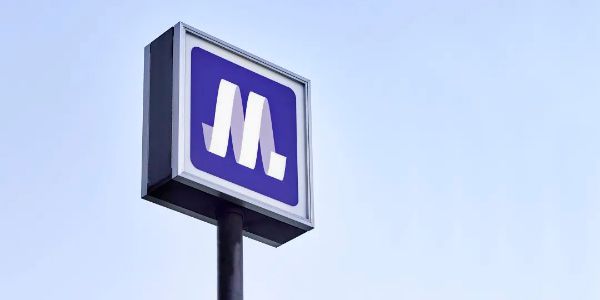
面对客户的致命三连,资深大叔教你从容应对
色部义昭的设计给我的感觉可以总结为两个字:“清爽”。这种清爽不只体现在画面表现出的自然的、恰到好处的感觉,还能从中看出设计背后的设计思维同样清晰,明朗。
相信他的思路会为你处理日常工作带来灵感。首先,我们就看一下他是如何与客户沟通的,这个经验你一定用得上。
我在色部义昭应对客户的心得中提炼出了三个点,这三点一定也是你常会遭遇的来自客户的三连暴击。
有些时候客户自己也不清楚自己要的是什么,这个时候帮助客户找准目标是我们设计师最重要的工作之一。我们需要在充分了解项目背景的前提下,帮助客户理清思路,规划一个方向。在开始动手设计之前,务必与客户达成一个清晰的共同目标,否则无限改稿就在不远的前方等着你。
客户是贪婪的,而我们要学会清醒。我们要清楚地意识到,所有都是重点就是没有重点。而我们要找的重点是“客户、设计师和消费者三者之间共通的一点”,集中精力做好这个点才是我们和客户的共同目标。
客户给出的意见有时是合理的,有时也会在项目进行到一半的时候突然跑偏。这时我们不要为了快速得到客户的认可而盲目修改。因为一次跑偏过后跟上来的只会是二三四五六次跑偏。我们真正要做的是回到第一步,重新强调我们的共同目标,再来推进下一步的工作。
色部义昭1974年出生在东京附近的千叶县,儿时的色部义昭就是一个安静少语的小孩,喜欢一个人坐在湖边观察过往的行人、植物、昆虫之类的东西。优秀的设计师在观察力上的天赋似乎都在小时候就初见端倪。
毕业于东京艺术大学的色部义昭主修的是艺术,但硕士毕业之后却进入了原设计研究所,成为了一名设计师。入行之后他深深体会到虽然「艺术」和「设计」同样关于创作,但两者的本质有很大分别,因为它们的出发点相反:“由最初的创作契机方向来看,艺术和设计本来就是不同的。艺术是(创作者)由内向外创作的,而设计则是外在的,乃(创作者)基于大家的观感,例如按客户的需要,而产生出来的。”
日本共有34处分布在全国各地的国立公园,为了树立国立公园的品牌价值,并宣传普及其多样性和魅力,色部义昭为其设计了统一的标志系统。
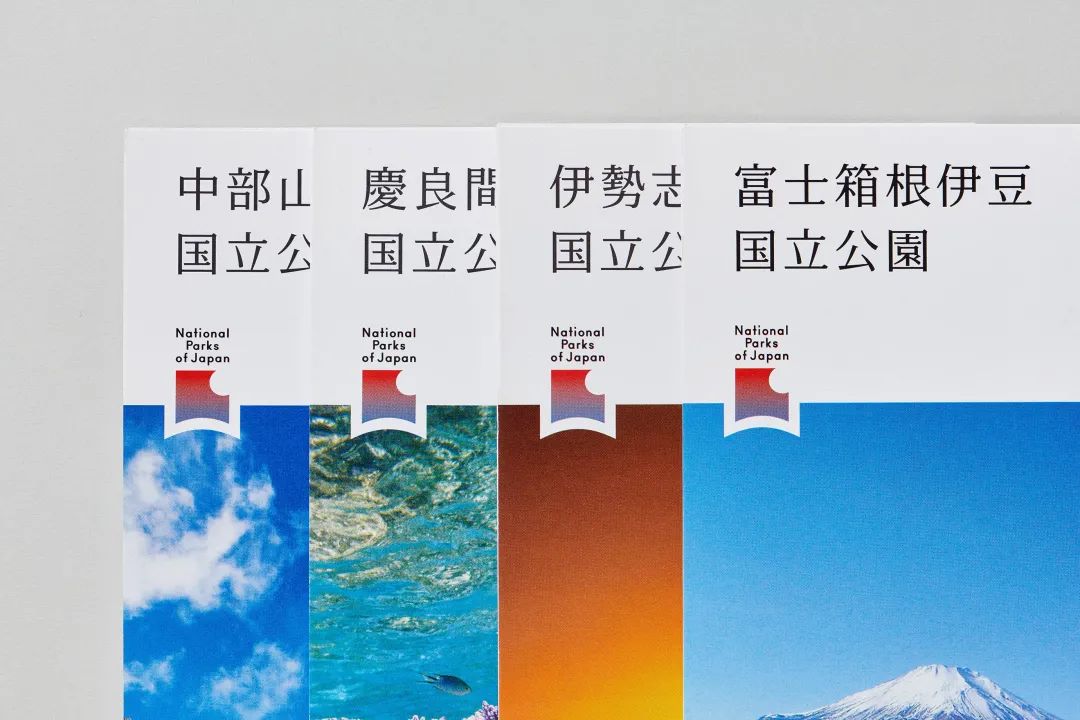
这个标志是我最喜欢的色部义昭的设计之一,初看时只是觉得简洁好看,并不明晰其含义。不过看过下面的动图之后,便可以用一个字来概括这个标志——妙。
标志采用太阳升起时的霞光设计,表现了极具日本特色的风景。同时,标志的外形还被设计成绶带的形状,当配在图片或招牌上时,有一种风景名胜获得表彰的效果。鼓掌。
大阪地下铁Osaka Metro民营化之后的全新CI设计,这是色部义昭最为人熟知的设计作品。
色部义昭的初始想法很简单,就是从Osaka Metro的名字出发,他希望将首字母“O”和“M”合二为一。从纯平面的角度来看似乎没有可能,但是色部将思维跳出平面的限制,发散到三维空间,问题就得到了解决。
色部义昭用一条旋转的纽带将“O”和“M”巧妙地结合在了一起,随着视角的变化,大阪的首字母“O”逐渐变成立体的 logo 的“M”,以此来表现 “Osaka” 的 “Metro”的主旨。同时,旋转的纽带也象征不断前进的列车,并呼应品牌精神“Change to Run,Run and Change”。
仔细观看动画能够发现,纽带并不是以单一的速度旋转,而是有急有缓节奏鲜明,因为这也是色部义昭的用心之处,他希望这个动画可以在大阪地铁站的屏幕上滚动播放,以此向人们传达,“虽然大阪是以快速流动而闻名的商业城市,但我的设计却不想表现这一特点,而是反过来,让大家在如此快速的城市,慢慢去享受、感受。”
对于这次的设计色部义昭认为,“Osaka Metro是支撑大阪市的基建设施,而大阪是国际大都会,这个标志的功用是让初到大阪的人也能一目了然;同时,考虑到这个标志在大阪出现的次数之多,我相信它需兼备环境设计的元素,以建构城市景观。”他希望大阪市民穿梭于城市的各处,看到这个新的标志也能从中获得启发,“标志的转变不但在于标志本身,也表示着时代进步,希望大阪市民自身也随之改变。”
色部义昭凭借大阪地下铁Osaka Metro的CI设计,获得了被誉为日本设计界最高荣誉的龟仓雄策奖。
图中是由六位空间设计师联合举办的一次设计展,因为是空间设计师的展览,所以在展览空间的设计上别出心裁,会场利用玻璃纱布折叠的方式,将每个设计师的空间隔开。
色部义昭从这种空间划分方式上得到灵感,将一张纸任意折叠五次,这样就将一个版面的空间划分成了六份,然后再将经过折叠后的纸张拿去印制成海报。这种方式完全呼应到了展览空间的设计,让一张平面的海报也有了立体的形状。想法虽然简单,但形式却很巧妙。色部义昭更是凭借这一设计赢得了2009 JAGDA新人赏。
Kachidoki View Tower是一栋52层的高层公寓,标志的设计思路是突出“高度”这一特点。为了体现出高的感觉,色部巧妙地采用了一个仰视的视角。只要你仰视它,立刻就有了高耸入云的感觉。
尤其是在夜间,公寓的细节隐去之后完全就是标志本人。
公寓的导视系统选择了AXIS的窄体字,是为了与标志图案共同传达一种高大的感觉。色部义昭认为,“仅仅用一个标志做一些与众不同的东西并不是一件简单的事情。这就是文字角色变得至关重要的地方。”有时我们选择字体是纯粹出于识别性考量,而有时字体的选择也是品牌价值传递的一部分。
Liquitex是一家颜料生产商,Liquitex Art Prize是一个公开参与的竞赛和展览活动,旨在鼓励下一代艺术家。
自2012年起,色部一直负责活动的平面设计并担任评委。他将Liquitex的标志比喻为笔刷的刷头,在纸面上画出颜色不同,长短不一的笔触。笔划开始的位置是一个字母P,在颜料重叠的部分还模拟了向下流淌的效果。
这种设计形式的巧妙之处在于它不是一个固定的标志,你可以把它理解为一个概念,一个动作或是一种玩法。它完美契合了Liquitex作为颜料商的身份,从实用性的角度出发又可以满足各种不同场景下的应用,玩出各种花样。也彰显了Liquitex迎合年轻人的自由活泼的印象。
Ichihara Art x Mix艺术节在我看来是一个极其有趣的妙想,它利用了车站和火车,以及沿途的四所废弃小学的场地和设施,以贯穿市原市的Kominato铁路作为整个艺术节载体。这种覆盖一整个地区的艺术节活动需要传递的信息量是巨大的。
色部将Kominato铁路标志性的红色条纹与圆润的AXIS字体相结合,制造了一套信息传递的系统。这套系统相当于建立了一个规则,它不拘泥于具体的内容,只要是红色的条状色块叠加上瘦长的字体就可以传播任何信息。
这套红色系统可承载的信息量大且醒目易读,它们以各种形式出现在艺术节路线的沿途,除了营造节日气氛,还充当了连接艺术节场馆的路标。鲜艳热烈,迎风招展。
红色的条带是艺术节的符号,当你发现周围出现了红色条带,就算只是橱窗上的一张海报,你也能知道自己走在艺术节的路线上,艺术已经离你不远了。
白鹤天空是著名的高档日本酒品牌——白鹤的旗舰产品,分为山田锦和白鹤锦两款。瓶身的造型以白鹤的立姿为意向。
色部义昭将白鹤颈部优雅的线条融入瓶身设计之中。瓶盖的部分也使用了相同的玻璃材质,这种材质上的统一性可让线条更好地延伸,同时也凸显了酒的高端定位。
这两款酒不同的瓶身颜色源于酿酒所用的两种不同的米,且这两款酒的酿造也分别采用了传统工艺与现代技术,因此,色部认为这种传统与现代的对比应该在设计上有与之对应的表现。
同时,为了丰富这两款酒的故事性,色部义昭将这两款酒设定为一对白鹤。为什么说是一对呢?你可以仔细看酒标上面的白鹤,真的是一对。所以如果你买了这两瓶的话,不要摆反了,会影响它们眉目传情。
在酒标的制作工艺上面,白鹤采用了类似水印的效果,仔细看上面布满了细密的网纹,这是一种复杂的日本传统制纸技术。还记得之前介绍过的“越乃寒梅”纪念款么?这种在酒标上面大动干戈的做法,除了体现酒的高端定位之外,同时兼具防伪功能。
看过上面的高端系列,再看这款同品牌的平价酒,整体设计呈现出极大的反差。这是白鹤250ml的纯米吟酿,是一款适合拿在手里饮用的酒。瓶身矮胖还有点可爱,颜色更加明亮,瓶盖也采用了方便饮用的螺旋盖。可见所有的设计目的都是为了打造新鲜轻快的印象,说明这款酒的定位也更年轻化。
这款面对年轻客群的纯米吟酿的设计我个人非常喜欢,色部义昭总是擅长用最简单直接的设计语言击中目标客群的心。
Naturaglace是一家强调以纯天然矿物质和有机植物提取物为原料的化妆品品牌。包装设计使用了低饱和度的水彩感觉的笔触,目的是体现化妆品不会为皮肤带来负担。
这个设计的切入点非常简单,但其中也不乏一些巧思,水彩笔触的颜色不是随意选取的,每一种颜色代表了一种天然原材料。比如蓝色代表水、红色代表刺玫果、黄色代表沙棘等。因此你会发现不同产品的包装上使用的颜色会有差异,因为每一款产品使用的颜色都代表了它所含的天然成分。
颜色的不同可以用于不同产品之间的区分,而低饱和度的应用可以让所有产品摆放在一起时又能呈现出和谐的统一感。相信这一组放在展柜上一定能从一种妖艳产品中脱颖而出。
去淘宝看了一下,这个牌子的口红两百多一支,不知道这价格算贵么?
草间弥生美术馆是一栋位于东京新宿的五层建筑,2017年10月1日正式开馆。美术馆的形象设计由色部义昭担任。
标志部分的字体设计源自草间弥生的亲笔签名,其中大写字母“Y”造型特点最为鲜明。这套基于签名的字体被应用在了美术馆的所有设计之中。整个美术馆的设计语言采用了与草间弥生的缤纷世界截然不同的纯白。就像一张空白的画布,让草间弥生的作品在其中成为绝对的主角。
由于美术馆采取的是每天四批次的参观制,每批次限时九十分钟,因此导视部分通过简单明了的图形为观者规划出了一条明确的单向动线。从一楼开始沿着楼梯一路参观,到达顶层后直接乘坐电梯返回一楼。
标志性波点元素被应用为辅助图形,让整套VI系统极具识别性,远远一看就知道是草间弥生。
其中手提袋的设计很巧妙,在放入内容物之后,波点元素会被衬托得更加醒目。
这件文化衫的设计就见仁见智了,我倒是能接受,不过对于有些人来说,应该会引起生理不适。
这个案例真实得不像话,为东京艺术大学设计新的识别系统。东京艺术大学之前文章中已经多次提到了,日本艺术类第一学府。为它设计东西已经压力够大了,结果甲方还要提“无理要求”。
图中的三个元素分别是:学校的标志,制作于1950年,沿用至今已有70年历史;“东京艺术大学”这六个字是原校长的亲笔题字;再加上色部设计的英文名称。这三样东西凑在一起完全不搭,问题是它们仨哪一个也不能删去。这画面是不是像极了你的日常?色部面临这一窘境的时候,他想起了一位前辈——葛西薰。
市原湖畔美术馆位于东京以东50公里千叶县的市原市,这间美术馆一个比较老旧的建筑物,希望通过新的视觉呈现为老建筑带来一种新的生机。
市原湖畔美术馆就如它的名字一样地处一个自然环境优越的偏僻之地,四周被水环绕。美术馆旁边的这汪湖水就是色部义昭的灵感来源。他用极简的长短不一的条状色块模拟了湖水波光粼粼的景象。
当这一汪湖水动起来的时候,你就更能理解什么是波光粼粼。
标志中的标准字采用了点阵的方式组合而成,并且这一规则被应用到了整个系统中的方方面面。不同的应用场景融入不同的巧思,造就了许多有趣的细节。
导视部分无论是图标还是文字,全部都是有点阵组成。
建筑外立面的巨大标志内部隐藏着由点阵组成的文字。
美术馆入口处,巧妙地利用了铁丝网栅栏原本就存在的点阵结构,用塑料卡扣在上面排列出文字的与图案。
在众多物品中,手提袋的设计格外有趣,标志上的横条被拆解成两部分分别印在透明手提袋的前后两片上。当其中装入物品后,标志的两部分被分开,隐藏在重叠部分的文字就会显现出来。
最后,想知道色部义昭的工作室招人,最看重什么品质么?